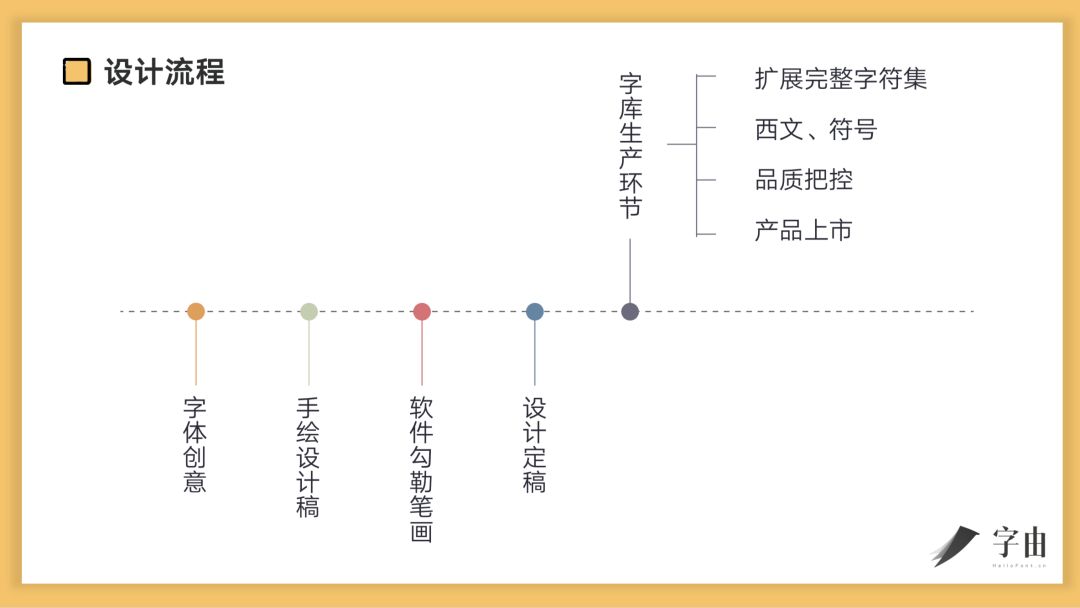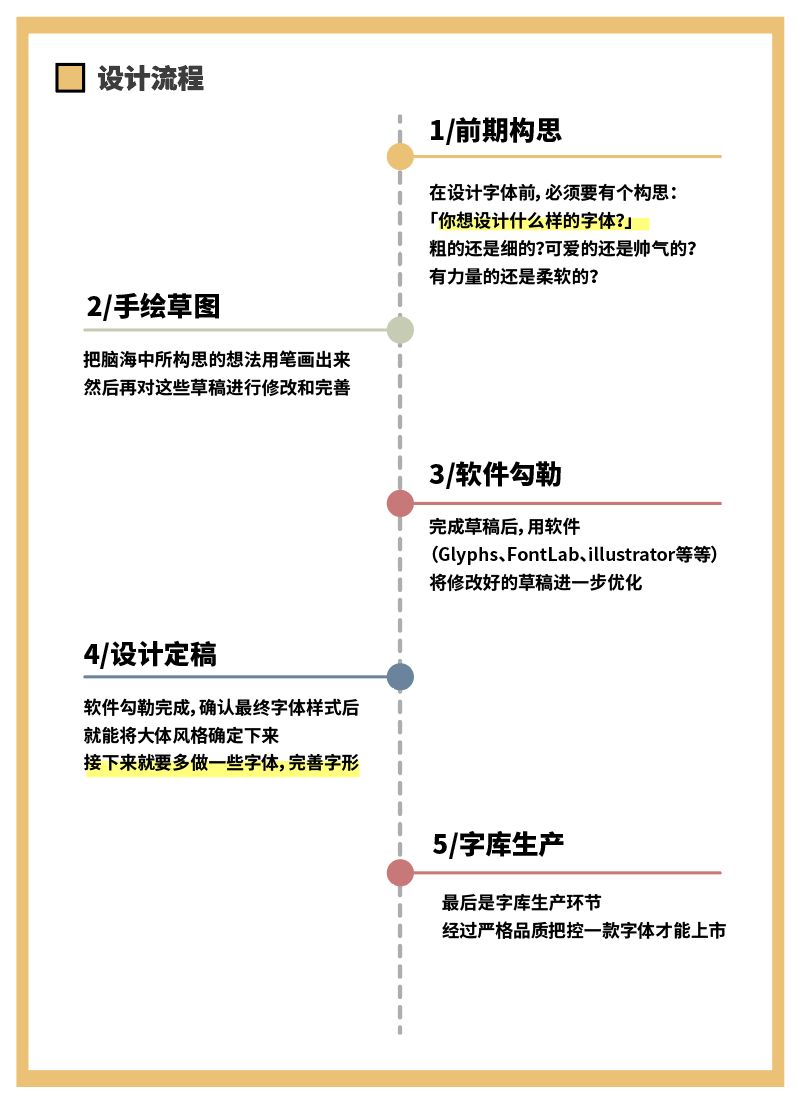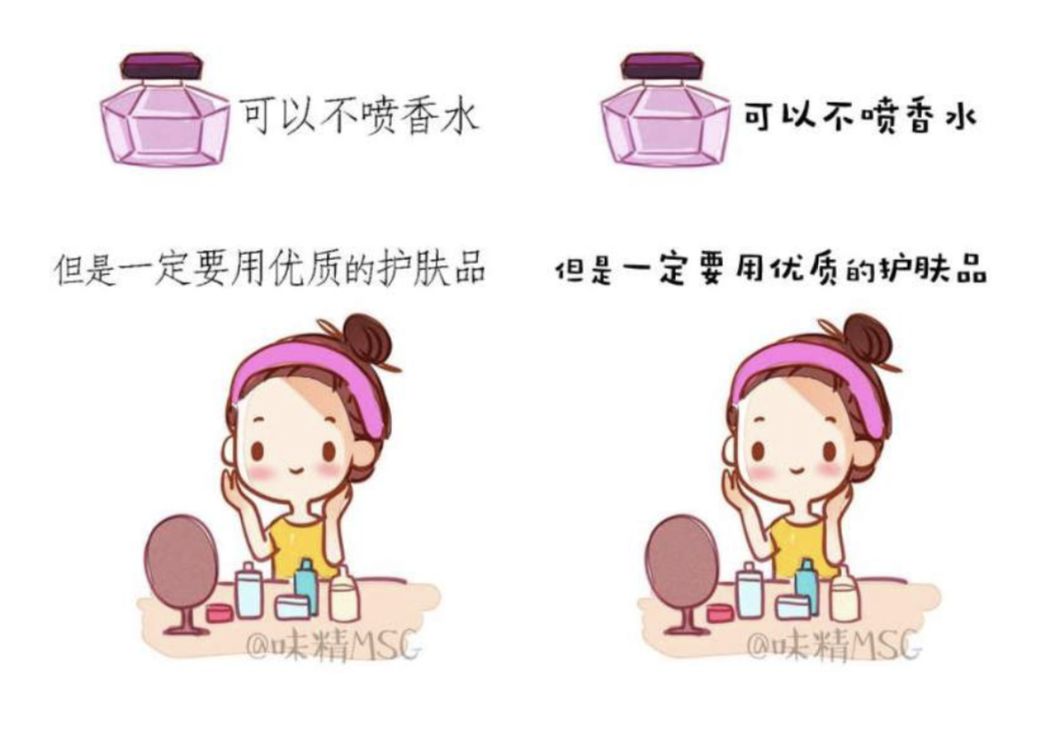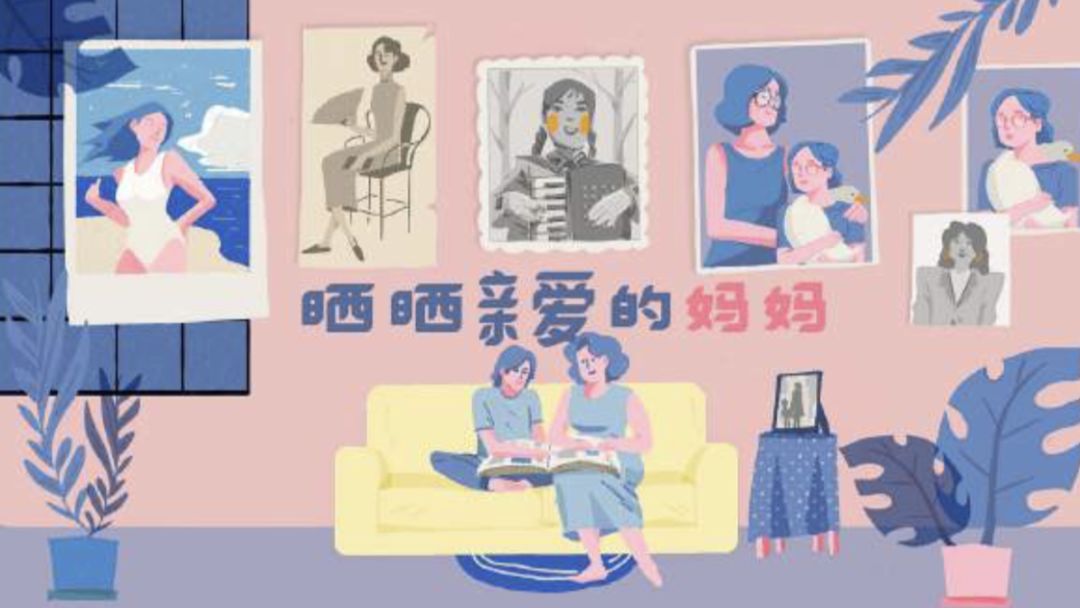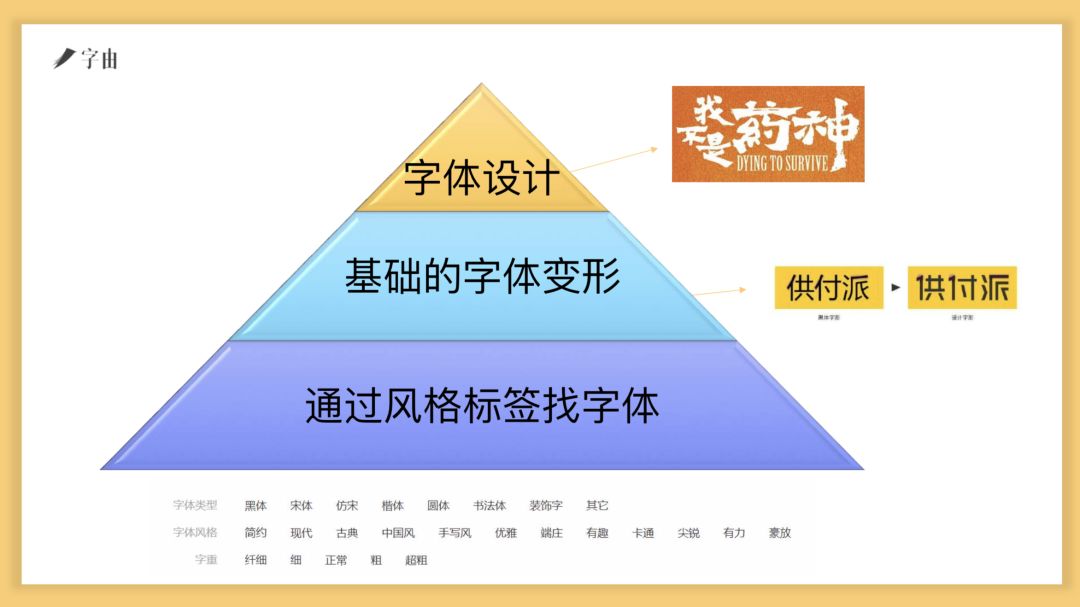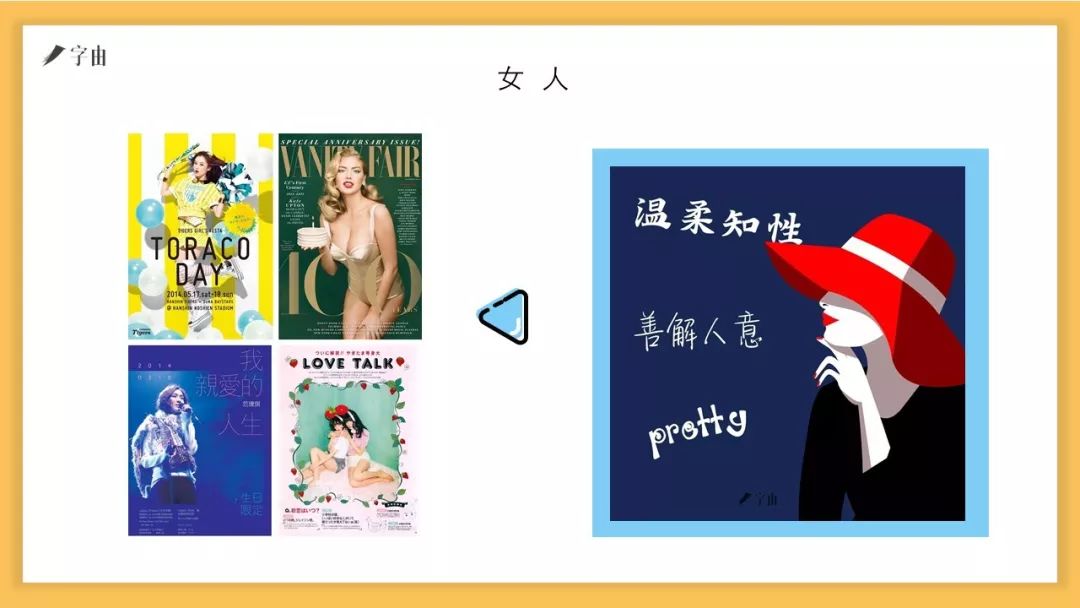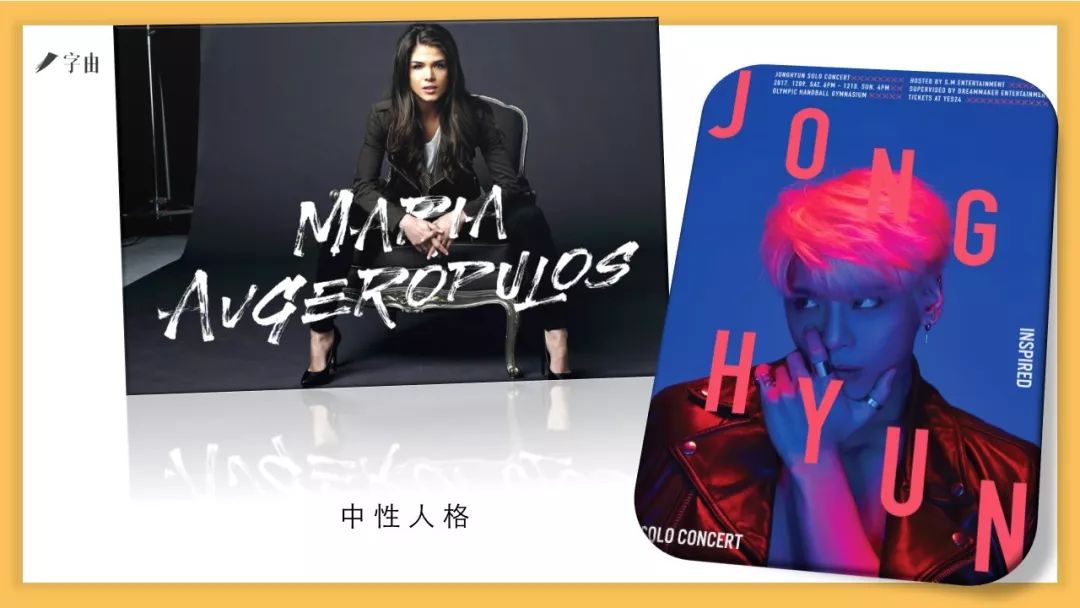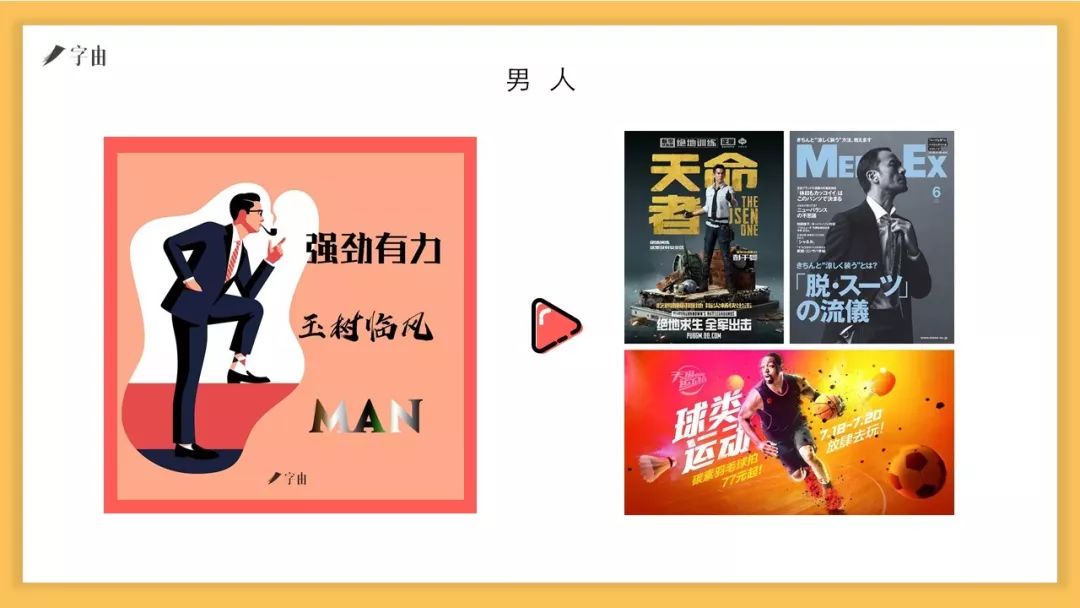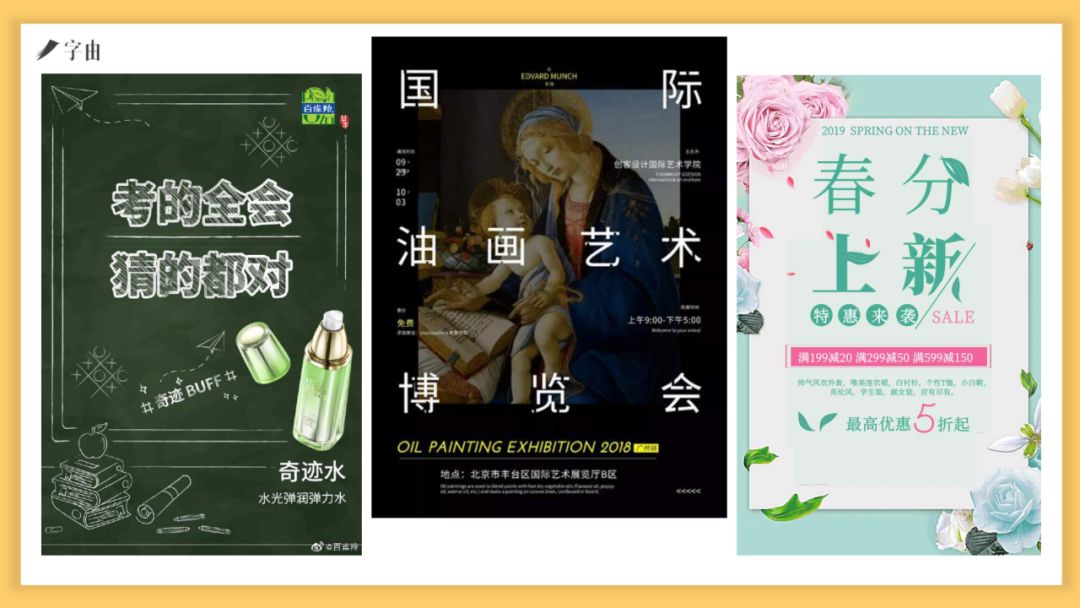
字体设计和搭配秘诀?我全帮你整理好啦!
字体设计基础
俗话说:知己知彼,百战不殆
想要游刃有余运用字体
那么就得先了解字体本身
接下来,先带大家看看一款字体
从构思到上市是怎么样的步骤
具体细节和流程是这样滴~
了解了设计流程
接下来要讲纯干货了
赶紧拿起小本本记下
基础字体&笔画
最基础的字体分为这几款:
黑体、宋体、仿宋、楷体
设计师最先开始做字体时
往往都会先做「永」字
因为永字比较有代表性
几个基本笔画它全占了
字体结构
字体结构也十分讲究
以下是字体的结构分类
间架结构
这是个重要的概念
简单来说就是字体的偏旁部首
是以什么形式组合起来的
比如「淼」是一个三角结构
我们就把一个正方格分为三部分
上面一部分和下面两部分
「模」字是左右结构
但在分析间架结构时需要
更加细致的拆分这个字体
所以将它分为左边的「木」
右边「草字头」
中间的「日」
还有下面的「大」组成
虽然字体都是在相同方格中制作的
但不同的字体也有不同的基本形态
比如国字,它就偏正方形
而人字明显就是一个三角形
对字体基本形态有初步认知
可以在设计时更好协调
偏旁部首与字体的整体关系
视错觉
人的眼睛虽然能洞察一切十分敏锐
但是也经常会受到环境等因素影响
会有被欺骗的现象和错误的感觉
这就是所谓的视错觉
简单举个例子:
所以字体设计时需要注意
线条对视觉的影响
字体重心
很多人会将字体重心误认为是方格中心点
其实并不然,字体重心是指字体视觉重心
对于整款字来讲,每个字只能确立一个中心
所有字都要以它为规矩,来调节高低和左右
同一款字,不同设计风格
其视觉重心也不一样
如果没有协调好重心
就会影响阅读
比如你想做一款高挑的字体
就适当把视觉重心提高些
想做一款敦实的字体
就把重心稍微降低些
字体布白
想让字体协调,观感舒适
光找对重心可不够
还要学会合理「布白」
简单说,就是合理安排文字内部空白
让字体看着更加舒适统一
汉字除了要求字体结构准确外
还要注意笔画组合间的露白空间
协调合理,不能过紧也不能过松
就拿下面图片为例
在笔画数与粗细都相等的情况下
第一排笔画粘连过多,看着拥挤
严重影响阅读,也造成整个
字形看着让人“透不过气”
而第二排经过调整后明显舒展多了
所以,大家在制作字体的时候
不仅要考虑字体本身的笔画细节
也不要忘了结合字体重心合理布白
提高整套字体的协调性和舒适性
字面&字间距
我们所用的字体都是在
相同的方框中做出来的
字面可理解为字体在框中的大小
字面占比例较大,字间距就会小
字面占比例较小,字间距就会大
字体分类
现在市面上的字体可谓五花八门
手写风、可爱风、书法风应有尽有
但分类时我们只需简单分为三种:
正文字体、艺术装饰字体、书法字体
要排版、印刷出版等
就要选择易读性高的正文字体
比如汉仪旗黑
而装饰字体和书法字体
延展性比较强,也比较有个性
适合作为大标题来引人注目
笔画统一
除了基础知识外,做字体设计的时候
还得注意笔画统一,例如下面这张图
不同字相同笔画的形态都是一样的
一套字库中,如果笔画风格不统一
就会造成整套字看着很别扭,不舒适
「细地」两字虽出自一套字库
但画圈处一个是提笔,另一个却是横笔
「个文」都是撇捺笔画,但「个」偏硬朗
而「文」则是软笔画结构
稍有不同都能造成整体不协调
由此可见,平常在设计中经常被忽略的字体
在设计规范上可谓极讲究,一点错都不能出
然而,上面还仅仅只是字体本身的设计
字体该怎么选,如何用也是一门大学问
接下来就由字由主编柚子给我们讲解以下内容
字体的选择与应用
我想大多数设计师都有这个苦恼
不知道怎么为自己的设计搭配字体
其实字体搭配主要有两个方式:
先字后图,顾名思义就是先从字体出发
再去延伸整个画面
图文融合度会比较高,不会造成做完图
文字无处安放的尴尬局面
在设计时也更清楚自己想要啥
但这种方法对设计师水平有一定要求
对字体风格没有什么概念的人
得先做出画面才知道要配啥字
就会先图后字
如最左边的「妈妈叫我不要学设计」
图片是一个豪放不羁恶包租婆形象
所选字体看着就比较粗旷有力量感
而中间的「晒晒亲爱的妈妈」就偏温情
搭配的也是比较圆润可爱的字体
如果要先图后字,要最先考虑
你的图想要表达什么东西?
想勾起用户什么样的情绪?
以此基础上去选字体会比较准确
具体怎么操作,要遵循下面两点
男人是粗、方、刚硬的风格
女人是细、圆润、可爱的风格
还有第三种人格,风格就要对调
才能符合规定场景
情绪
同样的一句话「I will always find you」
选不同的字体就会有两个截然不同的效果
一个十分温馨,而另一个格外惊悚
所以你就知道恐怖风就适合相对尖锐的字体
而温暖风,手写的字体再适合不过!
那具体的实际应用中
字体该怎么分类呢?
大概有下面三种
通过风格标签找现成字体
在现成字体基础上进行改造
自己根据主题设计字体
大多数设计师还是偏向于
使用现成字体或字体改造变形
但字体那么多,想找到合适的还是大海捞针
怎么才能选对字体?这4个W需要反复思考
给谁看?
不同人群喜好不同
90后可能更偏爱视觉效果“炸裂”的画面
而60后则会偏爱相对素雅、佛系一些的
用在哪?
要根据使用场景来配字,如下面的漫画
左边用宋体说明,整体违和感很强
而替换成偏可爱的手写体后
画面和字体就十分统一协调
表达什么个性?
以下俩案例主题是节日和美食
一个偏温馨,一个偏可爱
但第一排都用了较张扬的字体
给人一种“用力过猛”的感觉
换成第二排就明显舒服多了
所以当大家不知如何选择字体时
不妨通过关键词去联想
比如高级就是去掉多余装饰,笔画更简约
……
如何给字体加特效?
很多人在做设计时喜欢用免费字体
但免费字体又过于日常没有创意
不过其实这也是它的一个优点
就像服装的基础款,十分百搭
而且简单的造型也易于改造和变形
下面这三张图中都是
思源黑体和思源宋体
第一张结合热点做了个粉笔材质
第二张做了减法颇有股艺术气息
第三张则根据主题做了笔画替换
他们都做出了1+1>2的效果
看了以上内容,大家应该明白
字体本身就是一件设计作品
最后说一句
平常大家只要敲击键盘就能使用的字体
背后不知倾注了字体设计师多少心血
希望透过本次分享能让更多人了解字体